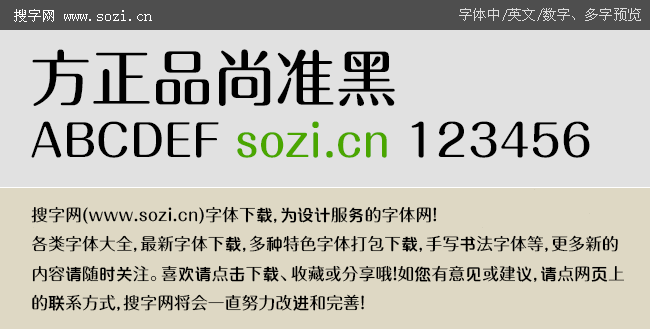
方正品尚準(zhǔn)黑簡(jiǎn)體
搜字網(wǎng)提供一款方正品尚準(zhǔn)黑簡(jiǎn)體字體中文藝術(shù)字體下載,方正品尚準(zhǔn)黑簡(jiǎn)體字體是一款由黑體為原形再加工的藝術(shù)字體,,整體效果十分出色,可用于藝術(shù)設(shè)計(jì)、包裝印刷、圖形設(shè)計(jì)等領(lǐng)域。